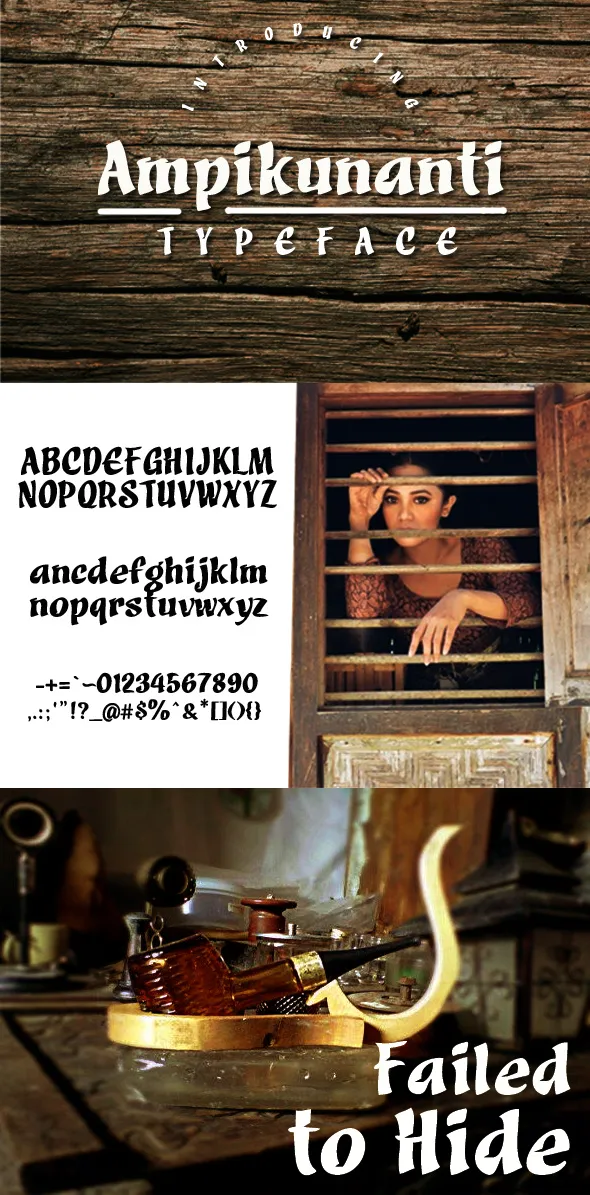
Ampikunanti Font – Download Grátis
A Ampikunanti Font é uma fonte divertida e colorida criada pelo designer Hamilton. Seu formato leve e alegre se destaca em qualquer projeto onde você precisa de um toque descontraído, seja em cartazes ou logotipos de empresas. Com seus traços levemente curvos e cores vibrantes, esta fonte é perfeita para adicionar um pouco de vida ao seu design gráfico. Se você está procurando por uma fonte que nunca cansa de ver na sua tela ou impressão, a Ampikunanti pode ser o item perfeito para incluir em seu portfólio. Visite a página do Graphic River para obter mais informações e adquirir sua licença comercial.